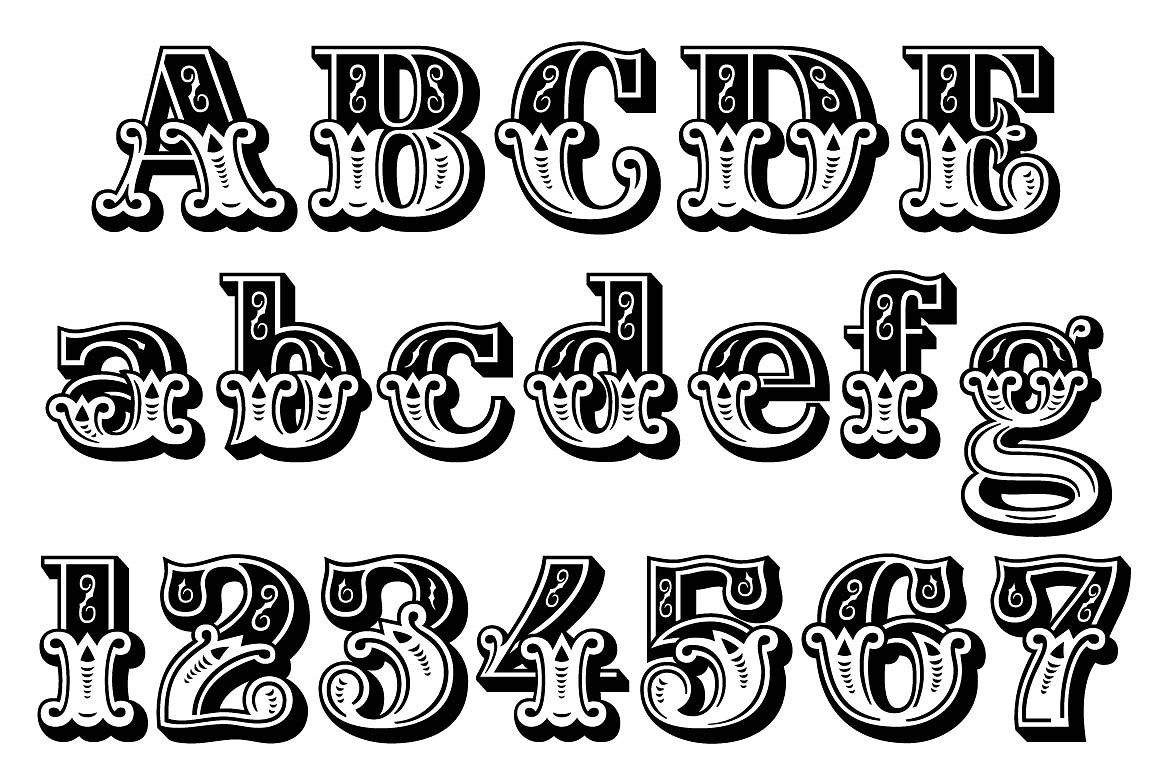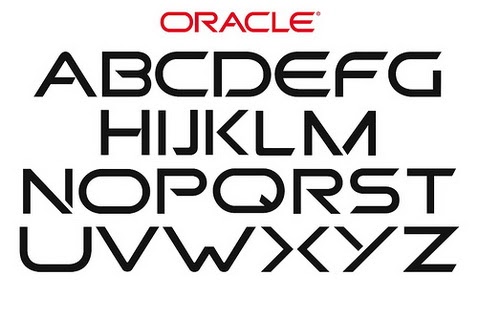
Русские шрифты для логотипа: Attention Required! | Cloudflare
принципы выбора, стильные и красивые виды
Логотип – это один из ключевых элементов брендинга, и нужно уделять ему много внимания, чтобы создать правильное восприятие. Решение о том, какой шрифт использовать, является критической точкой в любом дизайне.
Делая свой выбор, имейте в виду индивидуальность компании – это практическое использование логотипа и дизайна. В идеале любой выбранный вами шрифт будет уникальным для бренда, но, по крайней мере, он должен быть правильно лицензирован.
Значение шрифта
Бизнес-шрифты играют важную роль в информировании ваших клиентов и покупателей о том, кто вы как бренд. Шрифт может передать различные характеристики, которые вы хотите ассоциировать с вашим брендом. Вот почему так важно выбрать правильный «почерк».
Категории шрифтов
Вы можете легко выбрать один из доступных шрифтов для вашего логотипа, не читая длинные статьи. Однако у вас есть реальная возможность совершить ужасную ошибку со стилем, уровнем читабельности и, в конечном итоге, применимостью шрифта.
Как выбрать шрифт для логотипа: основные принципы
Должно быть очевидно, что шрифт, используемый в предложении, будет сильно отличаться от того, который используется в вывесках и лого. Сейчас мы можем выбирать из неограниченного количества шрифтов, и каждый из них выглядит лучше, чем предыдущий.
10 правил по выбору шрифта:
- Проанализируйте шрифты ваших конкурентов.
- Комбинируйте шрифты.
- Никогда не используйте два почти одинаковых шрифта.
- Избегайте использования несочетаемых шрифтов.
- Попробуйте использовать контраст выбранной комбинации шрифтов.
- Никогда не используйте более 2–3 шрифтов для логотипа.
- Шрифты разных размеров из одной семьи всегда будут выглядеть интересно.
- Откройте для себя тенденции, но при этом не игнорируйте классику.
- Людей привлекают простые вещи, поэтому старайтесь избегать использования сложных и трудно читаемых шрифтов.
- Узнайте все о вашей целевой аудитории.
Какие шрифты используют знаменитые компании
Например, известный бренд Кока-Кола используют рукописный шрифт с завитушками, ассоциирующийся с чем-то свободным и дружелюбным. В таком «почерке» даже прослеживается магичность.
У компании «Ситигрупп» лого написан в нижнем реестре шрифта без засечек, что подчеркивает доступность бренда.
Примеры шрифтов
Несколько популярных шрифтов.
Playfair Display и Source Sans ProPlayfair Display был разработан Claus Eggers Sorense и является шрифтом в традиционном стиле. Мы считаем, что он очень хорошо работает с Source Sans Pro, более простым стилем шрифта. Люди возвращаются к более традиционным стилям шрифтов, потому что они выглядят элегантно и дают ощущение совершенства.
Merriweather и OswaldЭтот шрифт очень легко читается и может быть легко изменен по ширине и высоте. С использованием его засечек и разборчивого текста, он наверняка станет главным шрифтом на новый год.
Разработанный Джульеттой Улановским, Montserrat – это современный, обтекаемый и разборчивый шрифт. Он выполнен без засечек и хорошо сочетается с Merriweather (шрифт с засечками).
Elsie и RobotoЭто красивый шрифт, созданный для прославления мира женщин. С с его плавными краями и засечками он очень элегантен. Это такой подробный шрифт, который нужно сочетать с чем-то очень простым. Шрифт Roboto идеален, он не отвлекает от заголовка.
Таким образом, при выборе шрифта для своего лого важно не копировать никого, а создать лично свое. Также не следует ориентироваться на свои желания. Необходимо узнать мнение людей, тех, кто будет покупать у вас товар.
Для удобочитаемости не следует лого нагружать сложными шрифтами, достаточно обойтись простыми и понятными. Не видитесь на ежегодные тренды, особенно, если вы нацелены на то, чтобы ваша компания процветала десятилетиями, а не год-два.
Так как сегодня то, что вы выбрали является модным, а завтра – нет.
Эти элегантные и универсальные шрифты идеально подходят для любого дизайна, от веб-сайтов до печатных материалов, и все они абсолютно бесплатны как для личного, так и для коммерческого использования.
Чтобы упростить процесс выбора и сочетания шрифтов, я привел примеры их использования, а также несколько вариантов сочетания. Наслаждайтесь и не забудьте поделиться с автором в Twitter (@noemistauffer), вашими примерами их использования!
Gangster Grotesk
Созданный Adrien Midzic, Gangster Grotesk – современный гротескный шрифт с угловыми концевыми элементами, которые слегка загибаются внутрь. Из-за этих причудливых индивидуальных штрихов гарнитура придает заголовкам и постерам уникальный внешний вид.